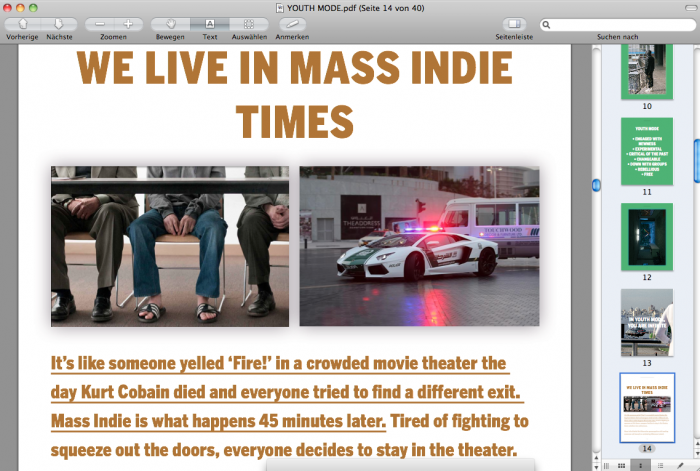
niemand erkennt die schrift / könnt ihr weiterhelfen?
vielen dank! ja scheint so - die besagte, aber leicht gestaucht.
ja, ich hab die pdf, jedoch zeigt mir die vorschau und auch die finder-information nicht die schrift an.
ok, also adobe reader schreibt, es ist die ''Benton Gothic Cond'' schrift. leider kann ich mir eine benton eh nicht leisten. trotzdem vielen dank beim lösen des rätsels!